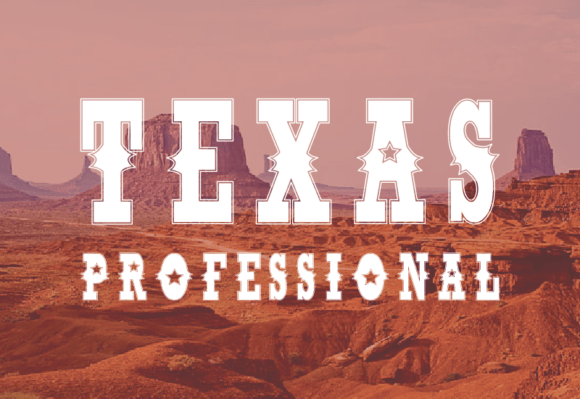
Texas Professional
Elaborado con precisión, Texas Professional proporciona vectores limpios, tipografía suave y una licencia comercial para tu tranquilidad.